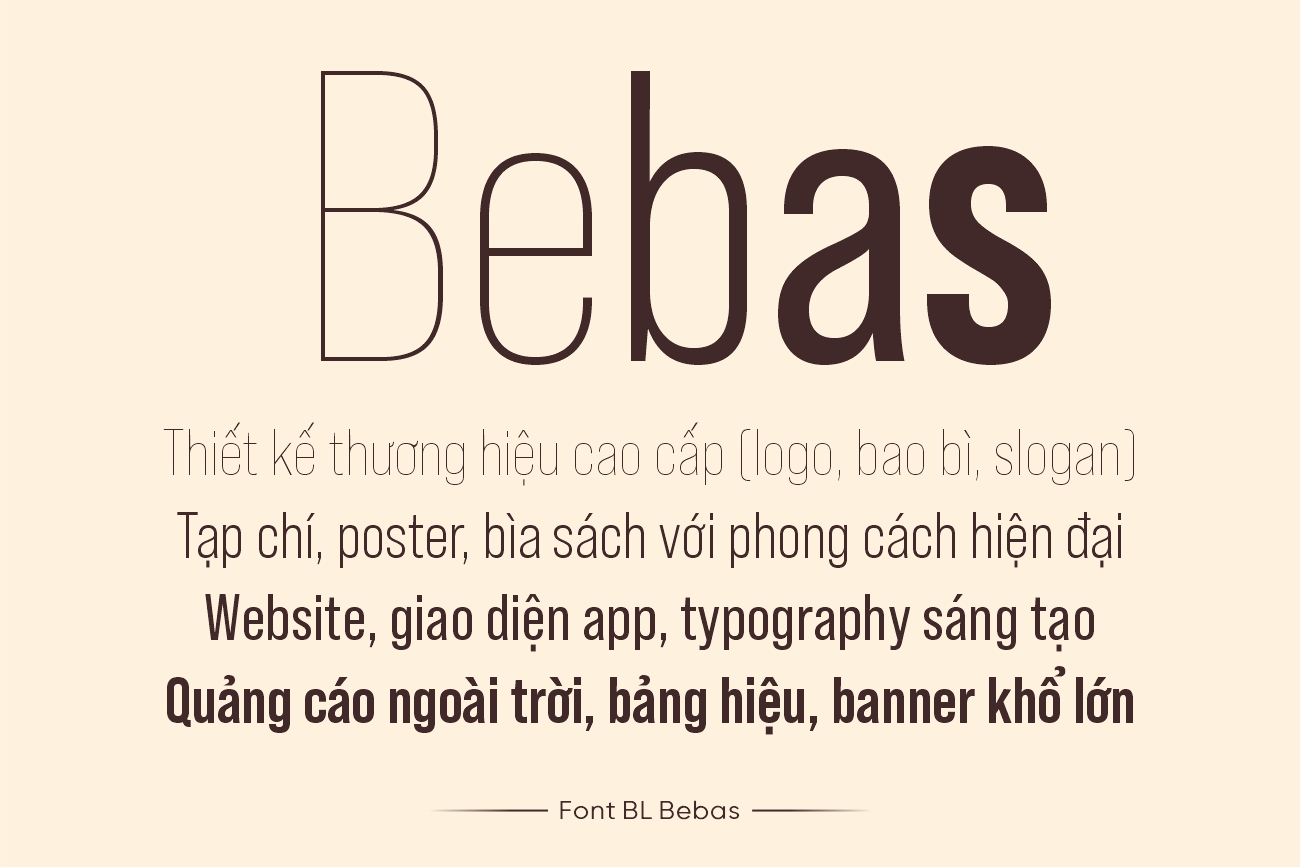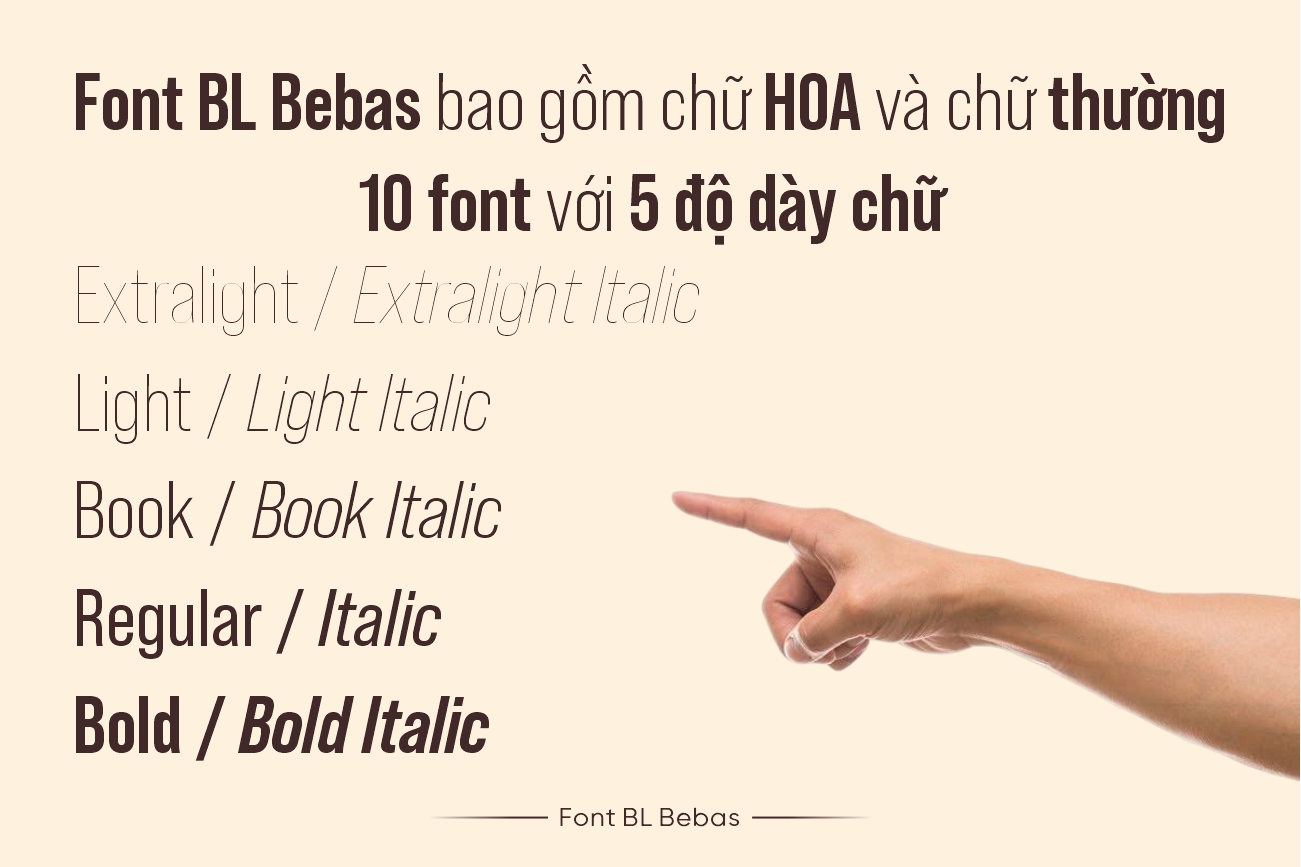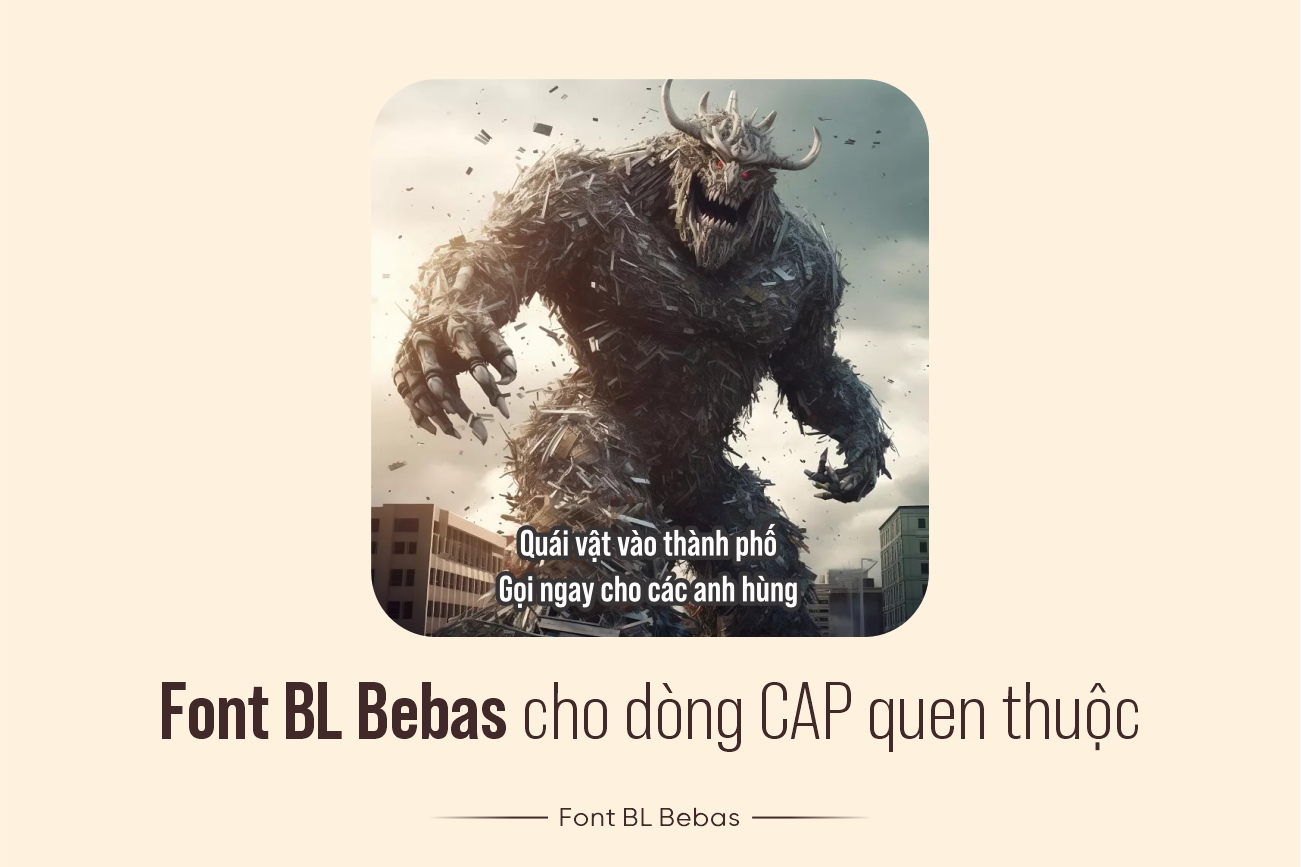
Font BL Bebas Việt hóa – Bộ font chữ hiện đại và đa năng cho mọi thiết kế
Font BL Bebas là phiên bản Việt hóa hoàn chỉnh được phát triển với mục tiêu mang lại trải nghiệm typography chuyên nghiệp và linh hoạt cho nhà thiết kế Việt Nam. Đây là kiểu chữ sans-serif mang phong cách hiện đại, tối giản nhưng vẫn giữ được sự tinh tế và cân đối trong từng đường nét. Với khả năng hiển thị sắc nét ở cả chữ hoa và chữ thường, BL Bebas mang đến cảm giác mạnh mẽ, tự tin nhưng vẫn dễ đọc và thân thiện.
Bộ font gồm 10 style tương ứng với 5 độ dày chữ, giúp người dùng linh hoạt trong việc kết hợp và tạo điểm nhấn cho thiết kế:
Extralight / Extralight Italic: thanh mảnh, phù hợp cho tiêu đề nhẹ nhàng, mang cảm giác tinh tế.
Light / Light Italic: mềm mại hơn, lý tưởng cho các layout cần sự nhã nhặn và thoáng.
Book / Book Italic: trung tính, cân bằng giữa mảnh và đậm, dễ dùng trong văn bản nội dung.
Regular / Italic: độ dày tiêu chuẩn, hiển thị tốt trong hầu hết các thiết kế từ web đến in ấn.
Bold / Bold Italic: đậm nét, mạnh mẽ, rất phù hợp cho tiêu đề, logo hoặc các dòng nhấn mạnh.
Font BL Bebas Việt hóa đặc biệt phù hợp trong các lĩnh vực thiết kế thương hiệu cao cấp (logo, bao bì, slogan), tạp chí, poster, bìa sách hiện đại, cũng như website, giao diện app, banner quảng cáo ngoài trời. Từng chi tiết của font được tối ưu để đảm bảo độ tương phản cao, độ giãn chữ hợp lý và khả năng hiển thị tốt trên mọi kích thước màn hình.
Bên cạnh đó, bản Việt hóa được chăm chút tỉ mỉ để đảm bảo các dấu tiếng Việt như ă, â, ê, ô, ơ, ư, đ hiển thị cân đối, không lệch hoặc vỡ nét. Điều này giúp BL Bebas trở thành lựa chọn lý tưởng cho các nhà thiết kế Việt muốn mang phong cách quốc tế nhưng vẫn giữ trọn bản sắc ngôn ngữ Việt.